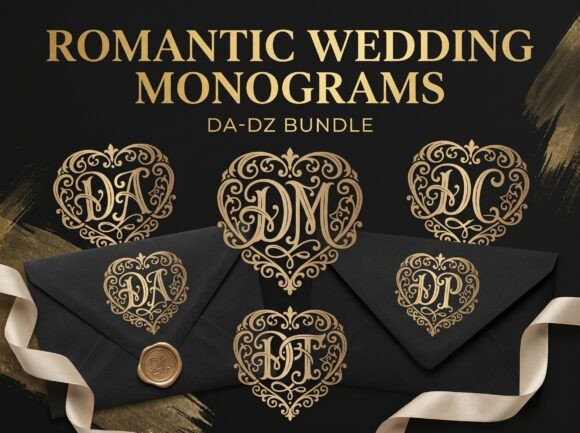
26 Romantic Wedding Monogram DA-DZ
Si buscas recursos de alta calidad como 26 Romantic Wedding Monogram DA-DZ, este paquete premium es una opción fantástica para tus proyectos creativos.
Elaborado con precisión, 26 Romantic Wedding Monogram DA-DZ proporciona vectores limpios, tipografía suave y una licencia comercial para tu tranquilidad.
Ya sea que estés creando productos POD (impresión bajo demanda), invitaciones de boda o gráficos para redes sociales, 26 Romantic Wedding Monogram DA-DZ es una opción ideal.